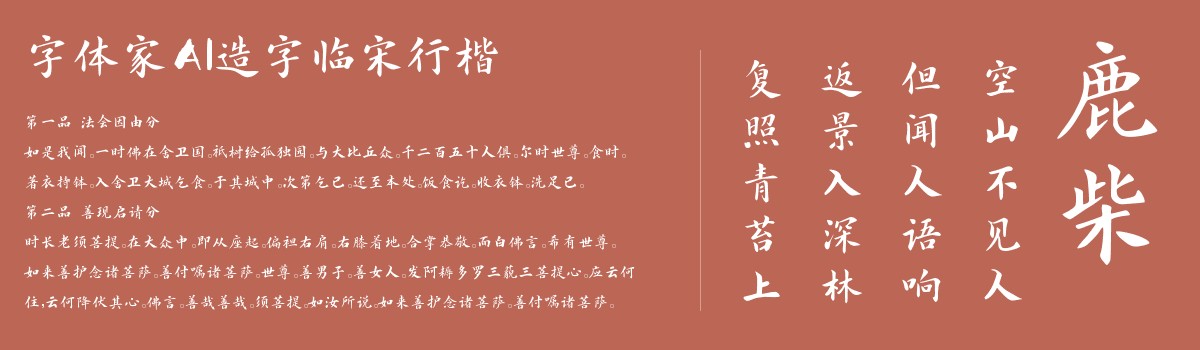
字体家AI造字临宋行楷
字体家AI造字临宋行楷是一款由字体家AI神笔造字生成的一款艺术字体,这款字体像温润的手写毛笔字,笔画起笔沉稳如轻按宣纸,收笔利落似笔尖轻提。横画微斜带舒展,像风中轻扬的丝带;竖画挺直却不僵硬,如竹节般有弹性。既有楷书的端庄骨架,又有行书的手写温度,书卷气中透着自在。比较适合用于艺术类装饰文字,海报、网页、广告设计,室内装饰,平面标题设计、食品包装、品牌标志等。